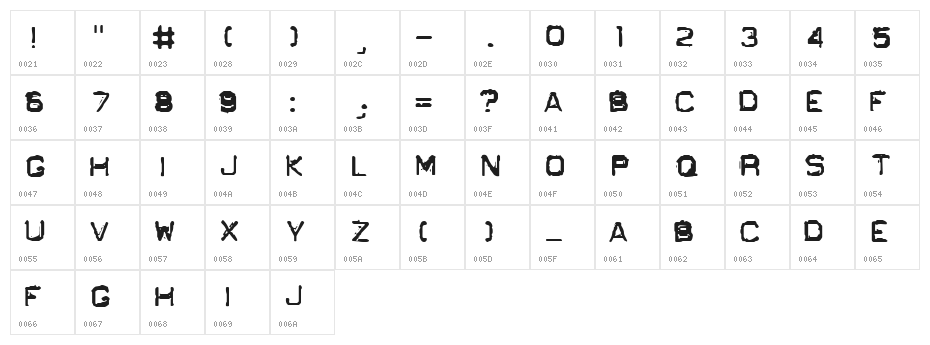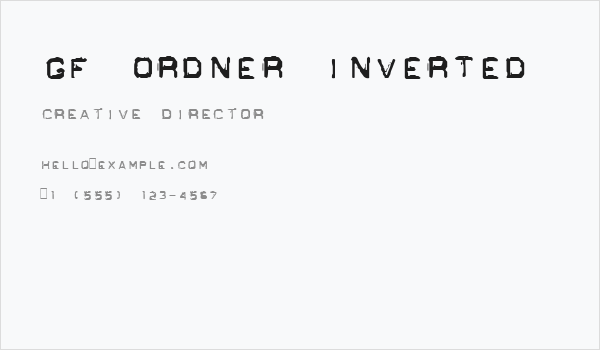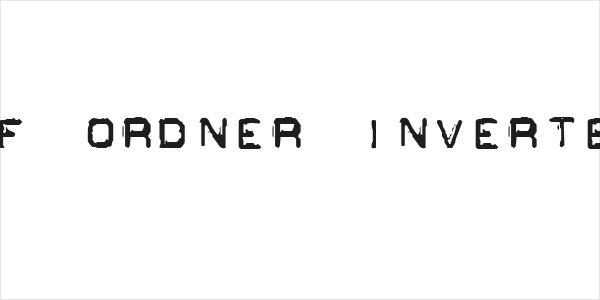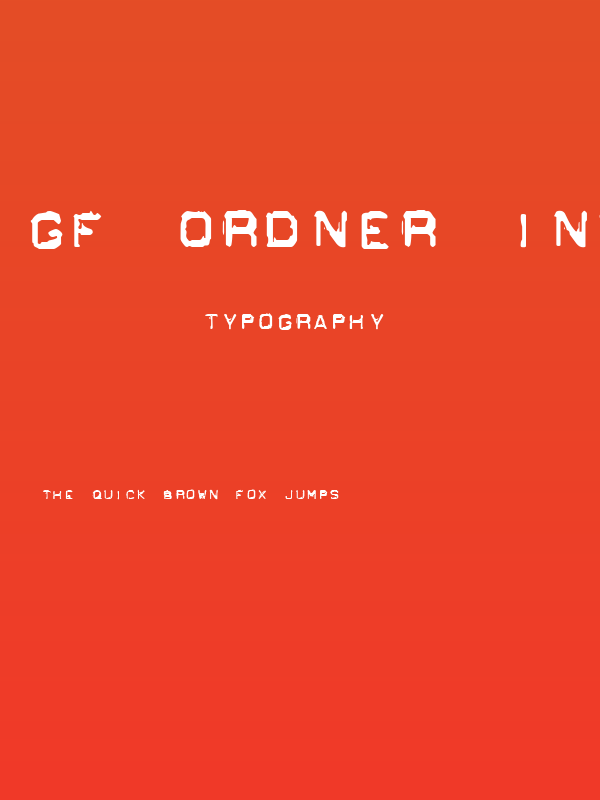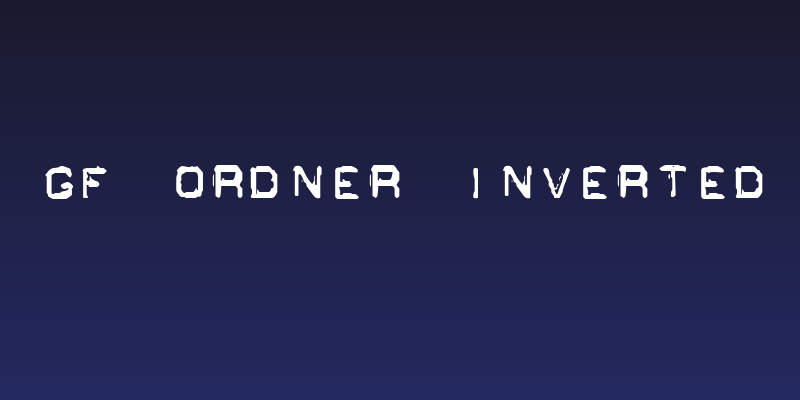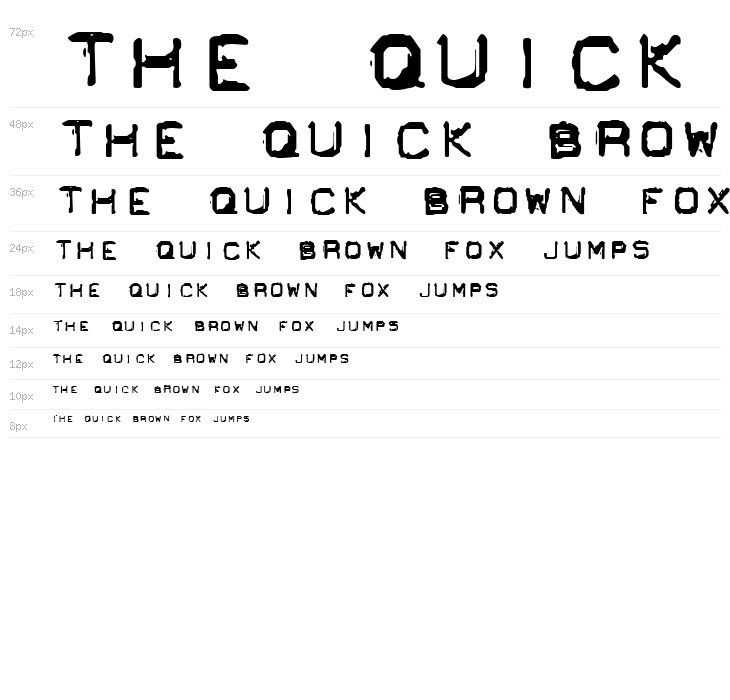
GF Ordner Inverted Font
| Stile generale | Vintage, Industrial |
| Progetti proposti | Ideal for posters, album covers, branding for edgy or vintage-themed products, and any design requiring a bold, textured look. |